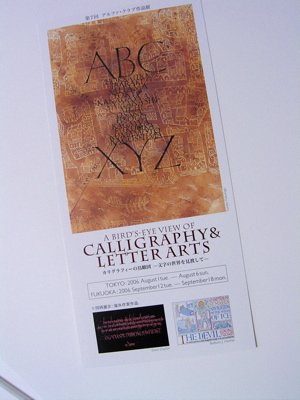
A Bird's-Eye View of Calligraphyーカリグラフィー作品展
今日から東京、京橋ギャラリークボタにて、アルファ・クラブ第7回カリグラフィー作品展が開催されます。
昨日は搬入日。朝から続々とメンバーが集まり準備作業開始。そして箱から出して飾り付け。昨日もmojitor-hさんが言ってた様に、この瞬間が一番楽しい!
「うわ〜!っ」とか「ひゃ〜」とか「ウーン・・・」と言った歓声やらため息がそこここに・・・・しばらく何年かなかった作品展なので出展者たちの意気込みと熱意がヒシヒシと感じられます。非常に完成度の高い作品の数々に頭がクラクラしました。
ホントです・・・・!!
特に2Fの奥の間には海外カリグラファーの作品がずらり。そこの空気を感じるだけでも行く価値はありますよ。そして日本のメンバーたちの力作も、素晴らしいの一言。日本で活躍している実力あるメンバーのこれだけの作品を一気に見る事の出来る作品展は、滅多にありません。絶対におすすめの作品展です。
そうです。遠くからこの作品展を見に来ても、1点あたりに換算すれば、非常に安いものなんです!なんと言っても素晴らしい作品が100点近くはありますから。
この夏イチオシの作品展、絶対見逃したら損ですよ〜。是非お越し下さい。
カリグラフィー作品展、早速行ってきました。
う〜ん、すごい!!夫々の作品が独特の色を持って饗宴しているようでした。素材や色あい、バックグランド、字体など、カリグラフィーの奥深さを改めて感じさせられました。多分、mojitor-hさんの作品であろうと思われるパネル張りの作品もしっかり見てきました!こんなに素敵な作品を無料で見せていただける作品展に感謝・感謝・感謝でした!!